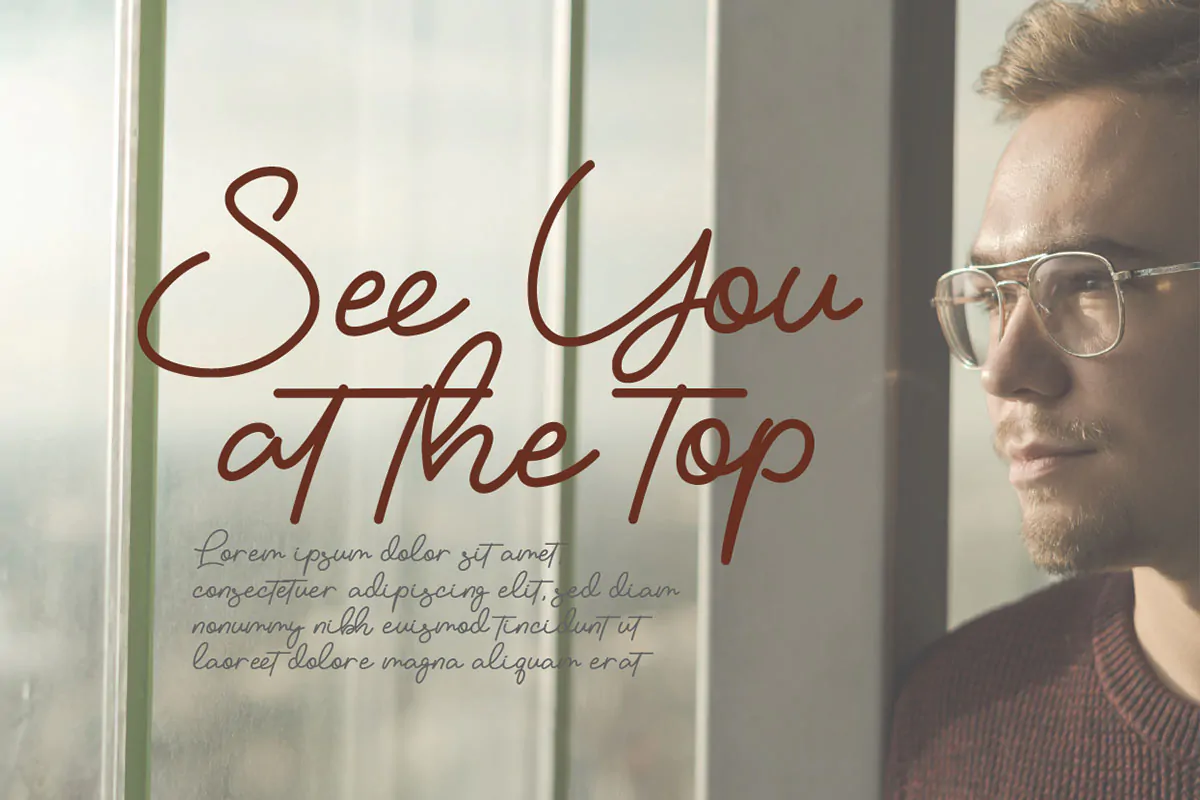
فونت دستنویس روان Vemina
فونت دستنویس روان انگلیسی
فونت دستنویس روان Vemina یک اسکریپت فونت انگلیسی فوق العاده زیبا است که مناسب جهت استفاده در طرح و پروژههای گرافیکی مختلف همچون طراحی انواع کارت تبریک، کارت پستال، کارت عروسی، طرحهای رمانتیک و عاشقانه ولنتاین، پوستر، کاور آلبوم موسیقی، بسته بندی محصولات، لوازم التحریر و … میباشد.